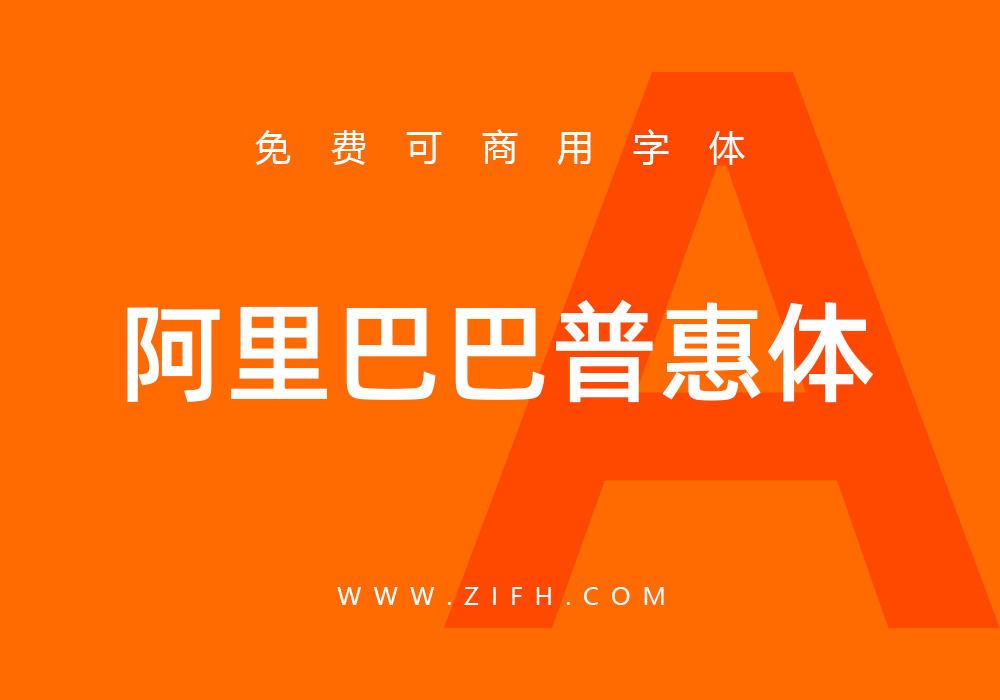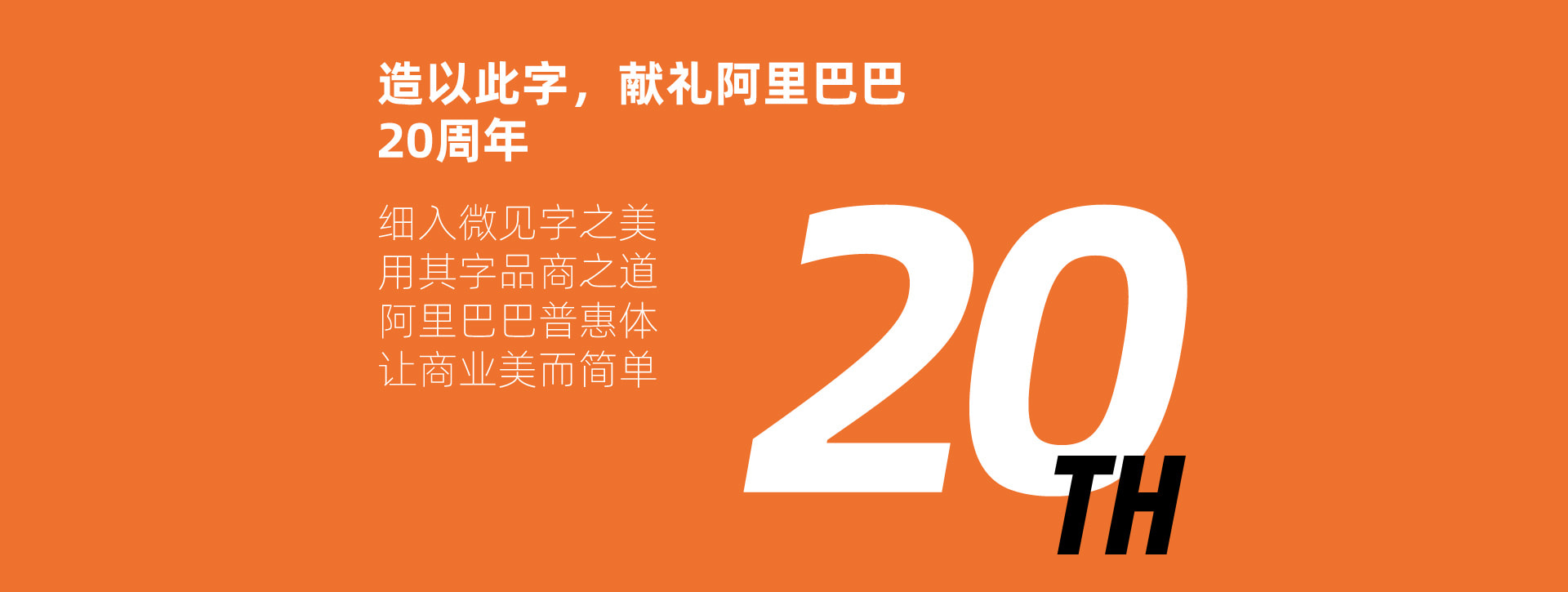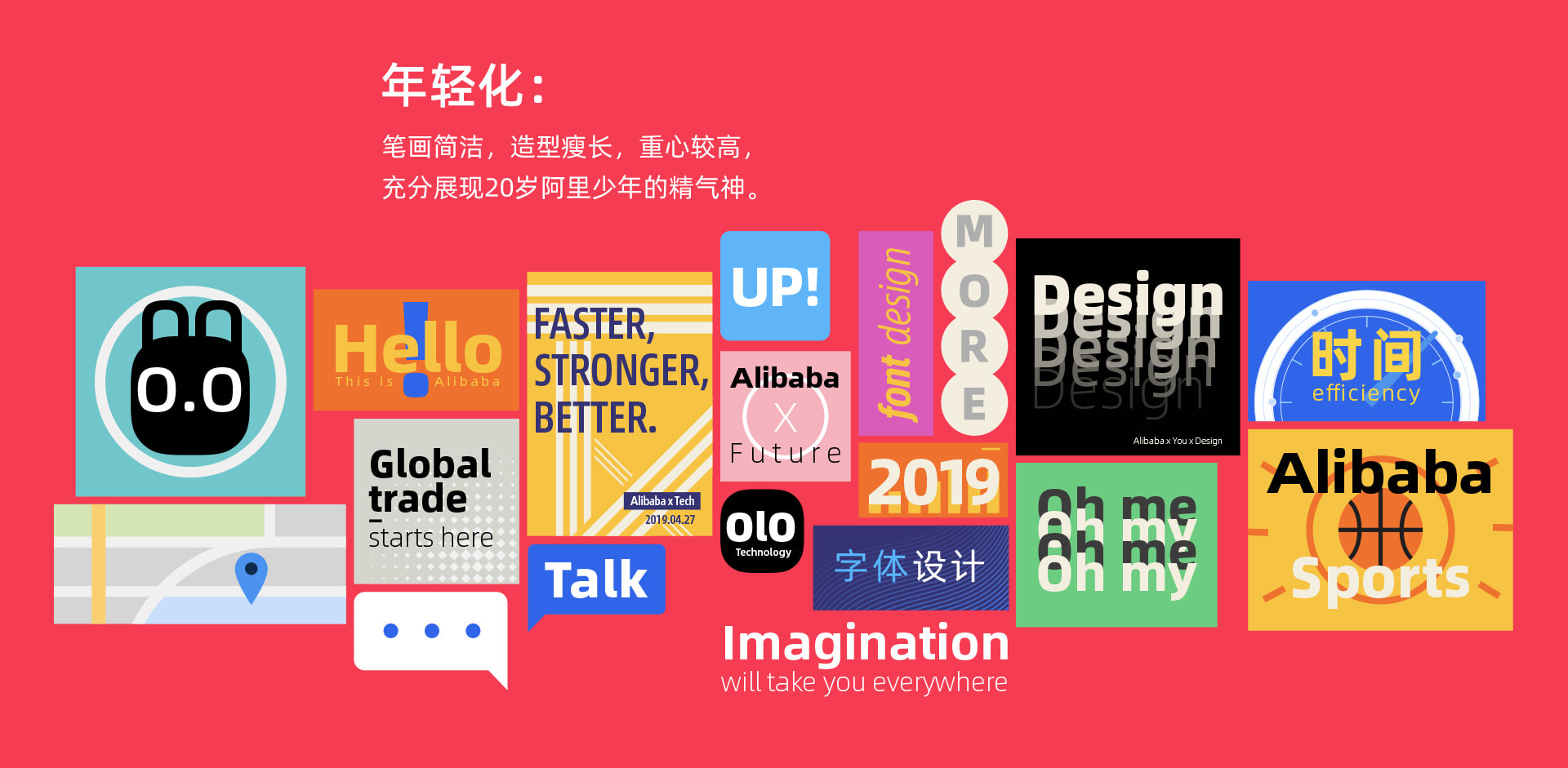
阿里巴巴设计委员会对外发布了一款名为“阿里巴巴普惠体(Alibaba PuHuiTi/Alibaba Sans)”的官方正文字体,这是一款由中国企业首次发布的可面向全场景使用的免费商用字体。
这一次可免费商用的阿里巴巴普惠体共收录116,895个全形汉字(含5个字重),西文Alibaba Sans共7,205个拉丁字母(2种风格、共11个字重),覆盖172个语种(覆盖大部分欧语国家),并可以满足阿里巴巴集团及其经济体公司在全球化业务下的多个应用场景需求。
阿里巴巴普惠体